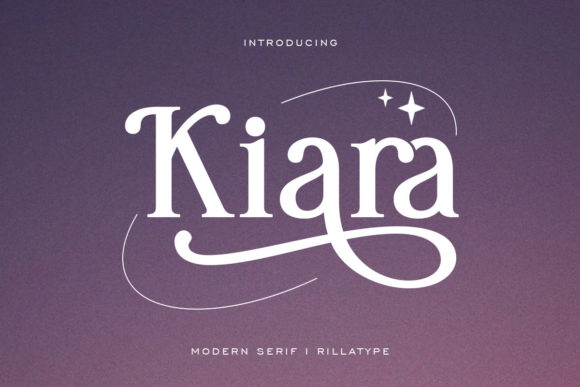
[Creativefabrica] Kiara Font (2021)
Kiara - это современный и элегантный шрифт с засечками.
Стильные чередования и лигатуры делают этот шрифт идеальным для любого проекта.